「色部義昭:WALL」展のギャラリートークから・その1
東京で増殖する文字
タイププロジェクトは、「色部義昭:WALL」展(2015年9月2日から28日までギンザ・グラフィック・ギャラリーで開催)に書体制作という形で協力しました。9月4日のギャラリートーク「東京のブランディングについて」には、色部義昭氏(日本デザインセンター、グラフィックデザイナー)、永井一史氏(HAKUHODO DESIGN代表、アートディレクター)と鈴木 功が出演。そこから書体についての発言をピックアップしてご紹介します。
色部:都市のサインプレートは、案内の機能を果たしているだけでなく、街の雰囲気を作っているものなのではないかと感じていて、そのなかで、書体のかもしだす雰囲気、あるいは書体の浸透力に注目せざるを得ません。文字というのはキーボードから打ち込むだけで、そのデザインがどんどん増殖していくんですね。そういうしくみを理解すると、ちゃんとした書体を用意して、その書体をサインに展開することで、街全体のデザインをスムーズに変化させることができるんじゃないか。
僕が東京という都市のサインデザインについて考えているとお話ししたところ、鈴木さんのほうでは都市フォント構想の一環として東京の書体について考えているということを聞いて、ぜひお手伝いしていただけないかということで、今回、東京シティフォントを提供してもらったという経緯です。
鈴木:都市フォントとは、簡単に言うと、地域の特色を取り入れた書体です。都市のアイデンティティを強化するようなツールとして、フォントを活用してもらいたい。そのような取り組みのなかで気づかされたのが、街のいたるところにあるサインの重要性です。書籍の本文用の書体にはたくさんの選択肢がある一方で、サインシステム用に開発されたフォントというのはほとんど存在しません。これは重要な欠落だという思いから、開発を進めていました。そんなときに、色部さんから「東京の街区表示板のための書体」というお話があったのです。
フォントのデザインを考える上では、街区表示板を「街々の表札」と位置づけました。そこに記される地名は、土地の来歴を示すものですから、東京シティフォントは、江戸から東京へとつながっている文化、伝統、好みを反映させたものにしたいと考えました。
色部:試作版の東京シティフォントを街区表示板に入れてみたときには、「あ、ほんとに東京だ」と見た瞬間ビビッときました。われわれグラフィックデザイナーは日々書体を使ってるわけですが、まだ誰も使ったことのない書体を最初に使うというのは、なかなか得られない感動的な体験でした。
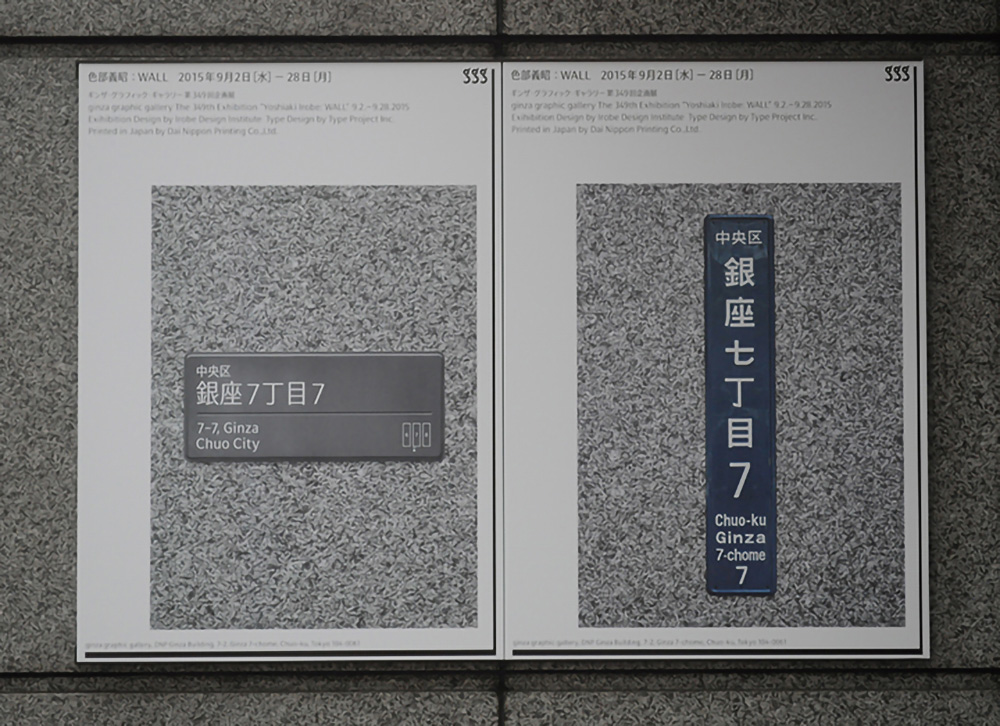
永井:色部さんのデザインされた街区表示板のフォーマットは、非常に抑制されたものですよね。そのなかで、鈴木さんの特徴的な書体が使われている。このあたりのバランスは最初から計算済みだったのですか。
色部:必ずしもそうではなく、ハッとさせられたという側面もあります。どんどん削ぎ落とす方向で考えていくと、東京シティフォントのようなデザインにはならないですよね。文字なんですけれど、華があるというか。ほんのりとした残り香みたいなものって大切で、この書体を通して街区表示板の貼られた周囲の空気が変わってくるような、そういう状況が浮かんできます。
永井:一般に表示板というと、文字も大きく太くというデザインになっていることが多いと思うのですが、このプロジェクトでは繊細な文字が使われていますし、文字のサイズも従来のものよりも小さいですよね。物理的なサイズと、そこから読み取れることの違いについてはどうお考えですか。
鈴木:それはまさに今日的な課題につながっていて、大声で話してもまわりの音にまぎれてしまう雑踏のなかで、たとえば鈴の音がピーンと通るように、街中の雑然とした風景のなかに置かれる書体には「大きな声」よりも「聞き取りやすい声」であることが求められていると思います。